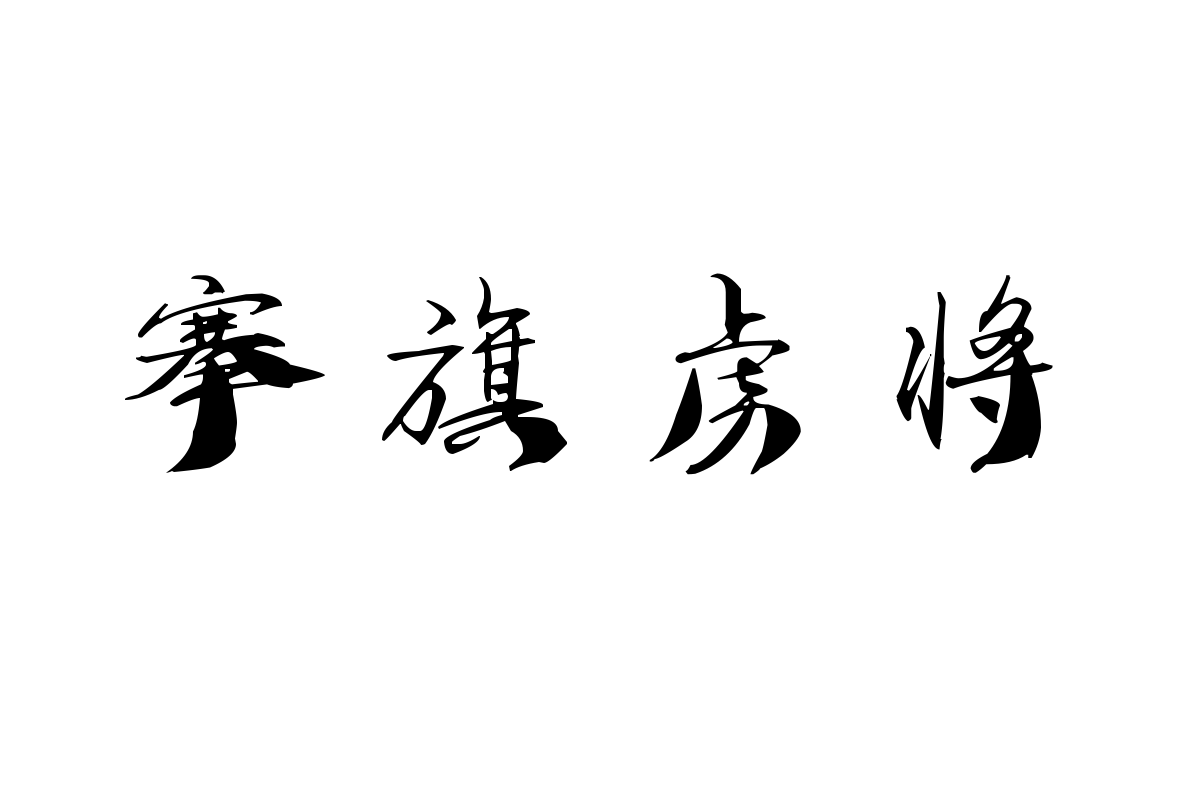
汉呈王天喜特色手写字体是一种具有浓厚中国传统文化特色的书法字体。这种字体以其独特的线条流畅、结构严谨而著称,给人以古朴典雅的感觉。
汉呈王天喜特色手写字体的特点如下:
1. 线条流畅:这种字体的线条呈现出一种流畅的美感,如同行云流水般自然。无论是横线还是竖线,都显得优雅而有力,给人一种宁静致远的感觉。
2. 结构严谨:汉呈王天喜特色手写字体的结构非常严谨,每个字的笔画都经过精心布局,使得整个字体看起来既和谐又富有层次感。
3. 古朴典雅:这种字体充满了浓郁的中国传统文化气息,给人以古朴典雅的感觉。它仿佛在诉说着历史的沧桑和岁月的痕迹,让人在欣赏之余不禁感慨万千。
4. 艺术性强:汉呈王天喜特色手写字体不仅仅是一种文字表达方式,更是一种艺术表现形式。它的线条变化丰富多样,既有粗犷豪放的气势,也有细腻柔美的韵味,展现了书法艺术的独特魅力。
总之,汉呈王天喜特色手写字体是中国传统文化的一种独特体现,它以其独特的线条流畅、结构严谨、古朴典雅等特点吸引了众多书法爱好者的喜爱。